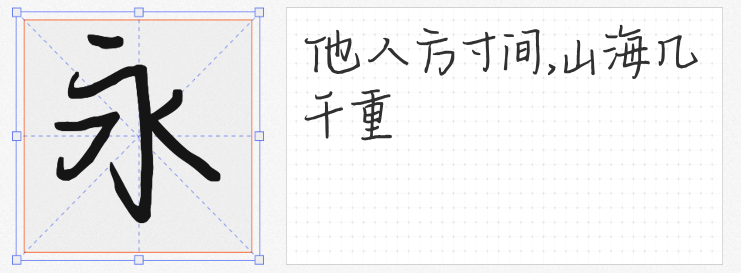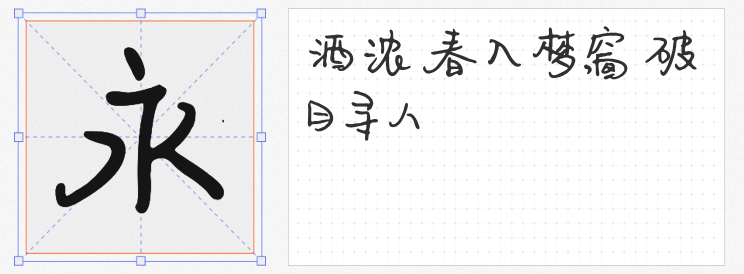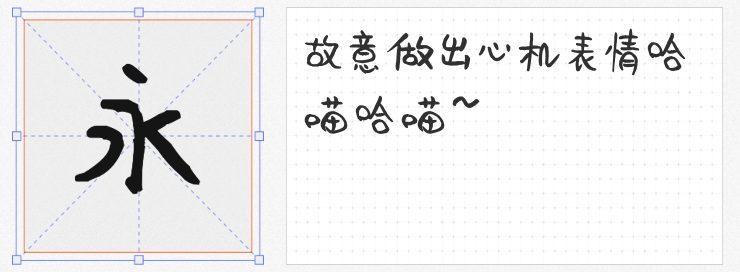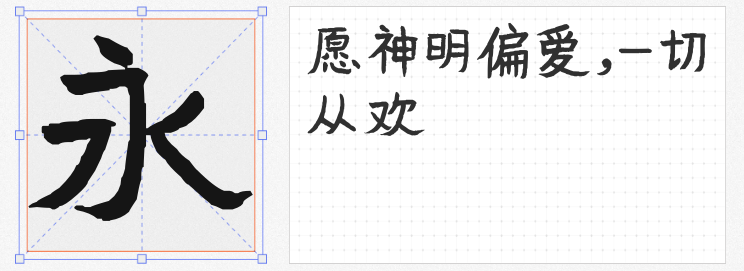
在设计领域,手写字体能为作品增添独特的温度与个性。今天就为大家推荐四款免费商用的手写字体,它们没有高深的书法技巧,笔画随意自然,仿佛带着学生时代的青涩与纯真。
平方青春体是一款手写艺术字体,线条均匀流畅,撇画向上微卷,如同青春里微微扬起的嘴角,带着一丝俏皮与灵动。整个字形瘦高,显得清新雅致,仿佛是校园林荫道上那个穿着白衬衫的少年,干净又纯粹。它非常适合用于各种文艺场景的文字排版,无论是文艺小清新的海报,还是充满诗意的书籍封面,平方青春体都能完美融入,营造出浪漫而文艺的氛围。
平方三生体笔触纤细,书写起来一气呵成,具有极佳的视觉感。它的笔画转折自然,如同舞者在舞台上轻盈地旋转、跳跃,充满了艺术的美感。这款字体在艺术设计、平面宣传设计、网页设计以及书法字帖等领域都有着出色的表现。在广告海报中,它能以简洁而优雅的姿态吸引观众的目光;在网页设计中,又能为页面增添一份精致与细腻。
平方萌萌哒字体充满了童趣,横的笔画略带弯曲,就像孩子写字时那不受拘束的笔触。字体结构略显俏皮可爱,仿佛是一个个活泼的小精灵在纸上跳跃。它非常适用于各种萌趣场景的文字排版,比如儿童用品的包装设计、卡通漫画的标题,或是可爱风格的社交媒体图文,都能让作品瞬间充满活力与亲和力。
平方追光体线条不均,却有着独特的韵味。笔触竖钩略带圆弧设计,仿佛是追逐梦想的脚步,坚定而又充满希望。它适用于各种文字排版设计,无论是商业海报、宣传单页,还是品牌标志,都能展现出独特的创意与个性。
这四款免费商用的手写字体,每一款都有着独特的魅力,能为你的设计作品带来不一样的惊喜。不妨在下次设计中尝试使用它们,让青春的书写记忆在作品中绽放光彩。